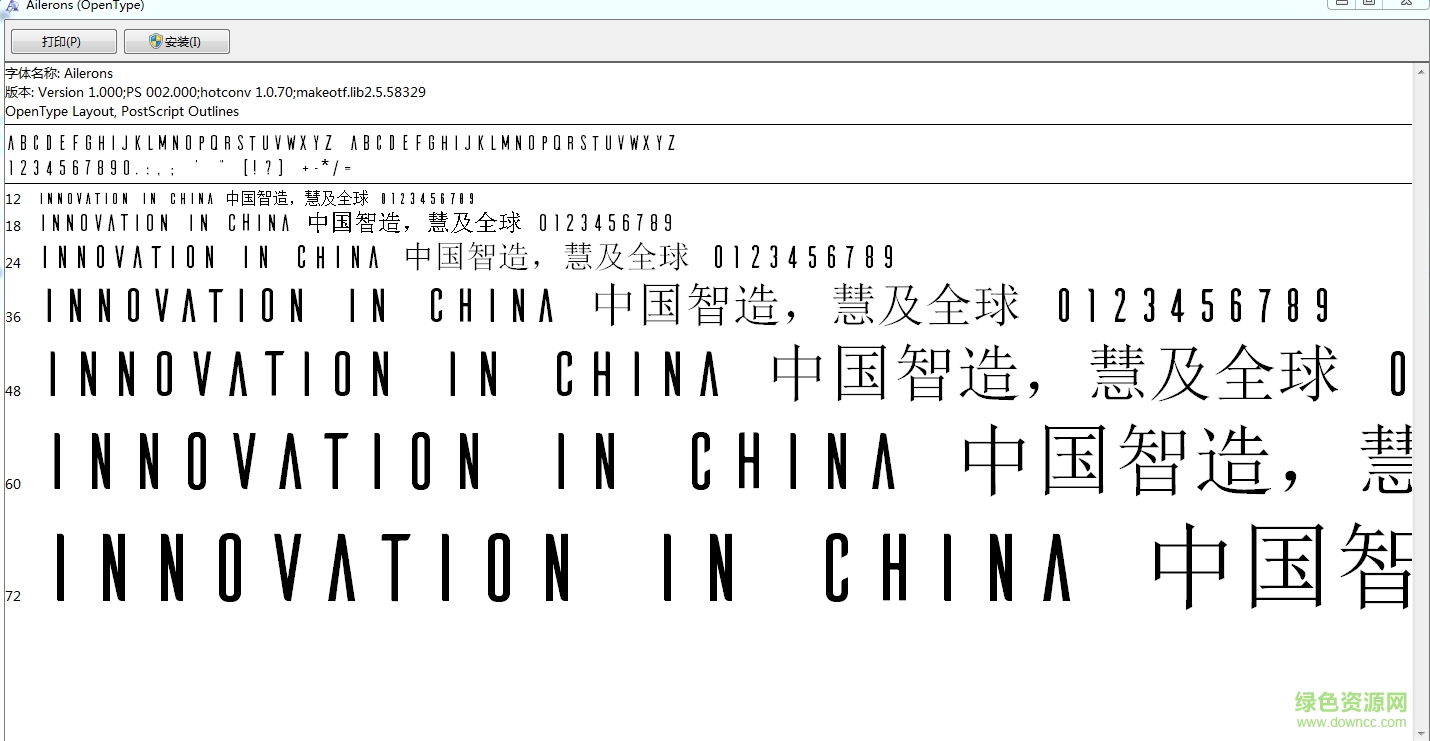
ailerons字體是一款簡(jiǎn)潔有力的英文字體,字體纖細(xì)勻稱,十分有特色,產(chǎn)品包裝、平面設(shè)計(jì)、ppt展示都可以使用這款字體,有需要者歡迎在綠色資源網(wǎng)下載!
Ailerons免費(fèi)英文字體字跡清晰,識(shí)別度高,適用范圍廣泛。經(jīng)過(guò)我們檢查,是無(wú)病毒軟件,請(qǐng)放心使用。具體字體效果詳見(jiàn)下圖。喜歡的小伙伴們快來(lái)下載吧。